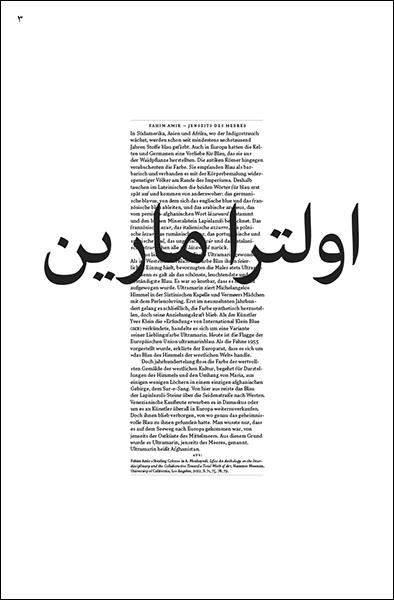
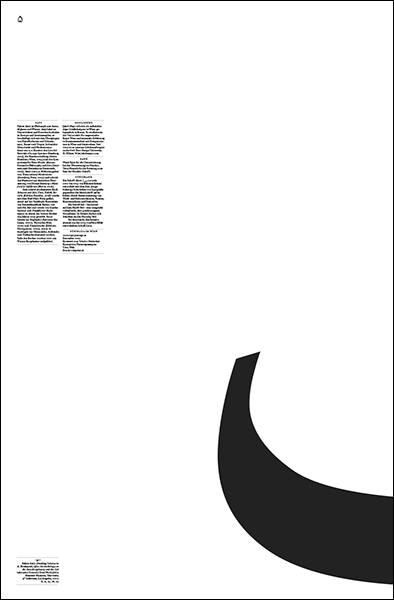
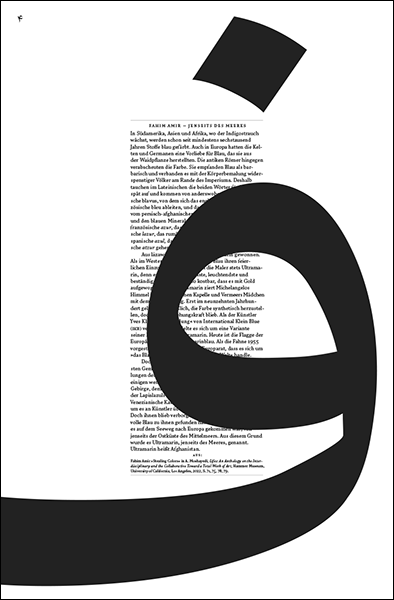
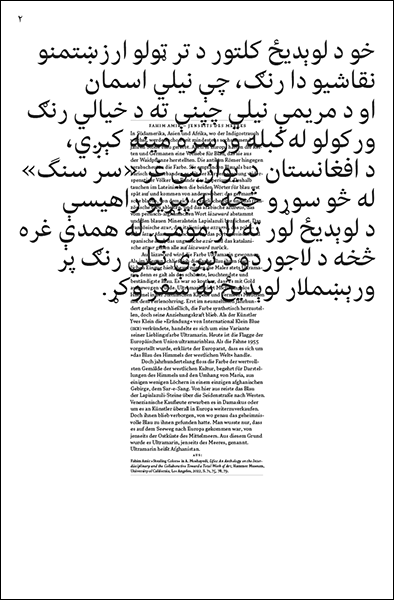
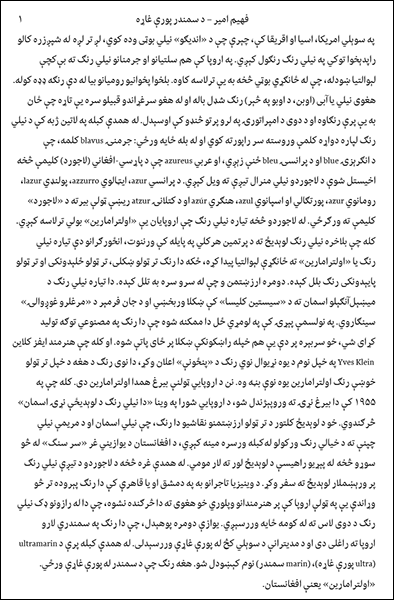
Text
Fahim Amir ist Philosoph und Autor, Afghane und Wiener. Amir lehrt an Universitäten und Kunsthochschulen in Europa und Lateinamerika; Er publiziert in verschiedenen Medien. Sein Buch Schwein und Zeit (Nautilus, 2018) wurde mit zahlreichen Auszeichnungen gewürdigt und ist in mehrere Sprachen übersetzt worden. Passage aus: Stealing Colors, erschienen in A. Moshayedi, Lifes: An Anthology on the Interdisciplinary and the Collaborative Toward a Total Work of Art, Hammer Museum, University of California, Los Angeles, 2022.
Gestaltung
Typografie
Die Schrift Harir wurde 2010 bis 2013 von Bahman Eslami entwickelt mit dem Ziel, einige bisherige Schwächen von Typografie gegenüber der Handschrift aufzuheben: durch Harmonisierung von Weiß- und Schwarzräumen, Punzen, Kontrastachsen und Diakritika. Die Schrift hat – basierend auf dem Naskh-Stil – eine waagrecht verlaufende, aber geschwungene -Grund-linie. In Details finden sich Anleihen an den Nastaliq-Stil. Der lateinische Zeichensatz stammt aus der 2013 von Peter Bi?ak entwickelten Schrift Lava.